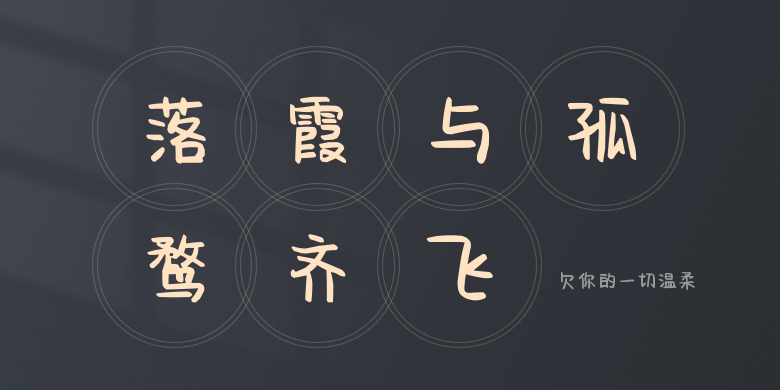
欠你的一切温柔
欠你的一切温柔,这款字体结构工整、笔画清晰,兼顾美观与易读性,适用于标题、正文、海报、包装、LOGO 等多种场景。字形优雅稳定,风格百搭耐看,适配日常排版与创意设计,让文字呈现更舒适、更具质感。欠你的一切温柔一笔一画,皆是细节,以均衡的比例、流畅的线条打造舒适视觉体验,字形端正大气,风格简约现代。无论是商业设计、品牌宣传还是日常排版,都能轻松驾驭,让文字更有格调与力量。欠你的一切温柔字体下载。